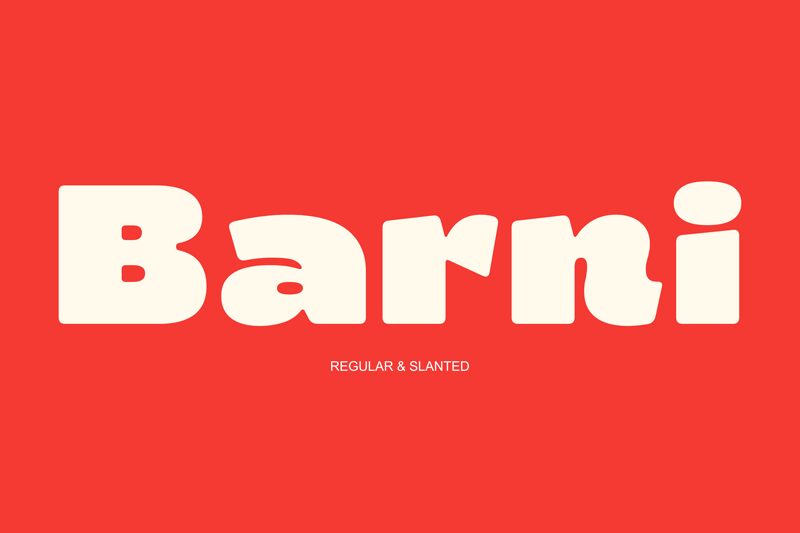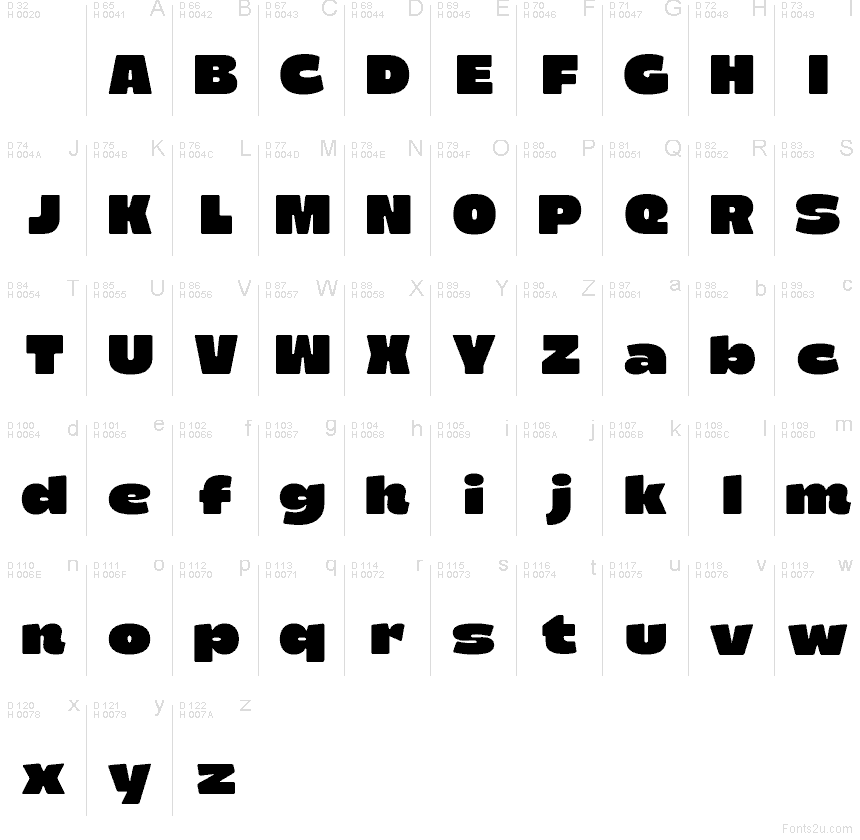
Barni Bold von Genetypeco ist eine kostenlose, moderne Display-Schrift mit einer weichen, wuchtigen Silhouette und einem leicht retro-inspirierten Charme. Die Buchstaben wirken aufgeblasen und freundlich, geprägt durch schwere, abgerundete Formen, tiefe Schwünge und verspielte Einkerbungen, die verhindern, dass das Gewicht zu starr wirkt.
Das macht sie zur idealen Wahl für Plakatüberschriften, Verpackungen, Musik-Artwork, Jugendmarken und Social-Media-Kacheln – überall dort, wo große Worte Wärme und gleichzeitig Durchschlagskraft brauchen. Als kostenlose Schrift eignet sie sich auch hervorragend für Logos, kurze Cover-Texte und Monogramme, da die breiten Formen und originellen Schnitte selbst kurzen Wörtern eine mutige, lebendige Präsenz verleihen.